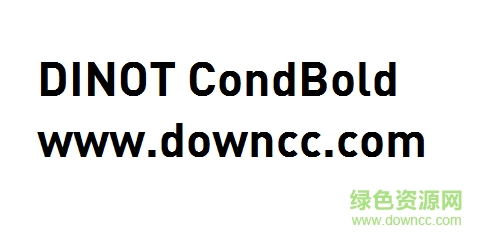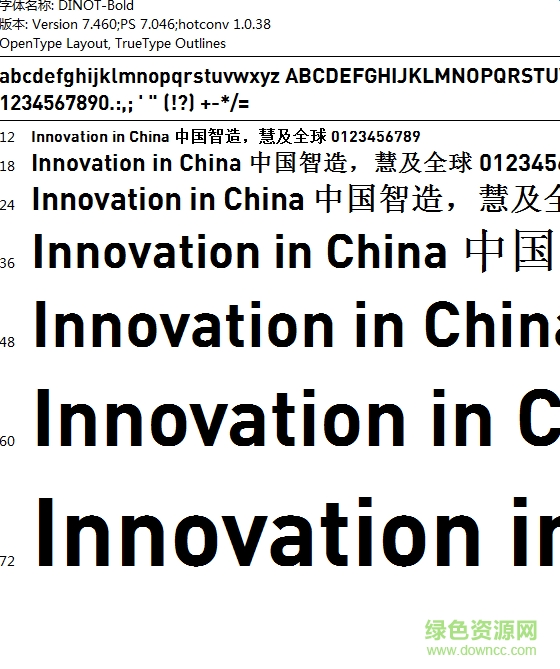
DINOT字體是一款粗黑系列英文字體軟件,該字體筆畫大方得體,十分正規(guī),整體效果比較耐看,適用于各大標(biāo)題內(nèi)容文章的設(shè)計(jì),更多好看字體盡在綠色資源網(wǎng)!
DINOT字體是一款應(yīng)用于藝術(shù)設(shè)計(jì)方面的簡(jiǎn)體英文字體,該字體筆畫粗獷,大字效果突出且引人注目;并且最大程度還原作者書寫字形,細(xì)節(jié)表現(xiàn)完整,且字庫(kù)完整,可以廣泛應(yīng)用于名片設(shè)計(jì)、新聞媒體、宣傳海報(bào)、ppt、影視制作以及內(nèi)容用字等領(lǐng)域。
DINOT英文字體是一類古典英文字體,字體筆畫一絲不茍,整體顯得非常酷炫大方,深受廣大年輕人喜愛!